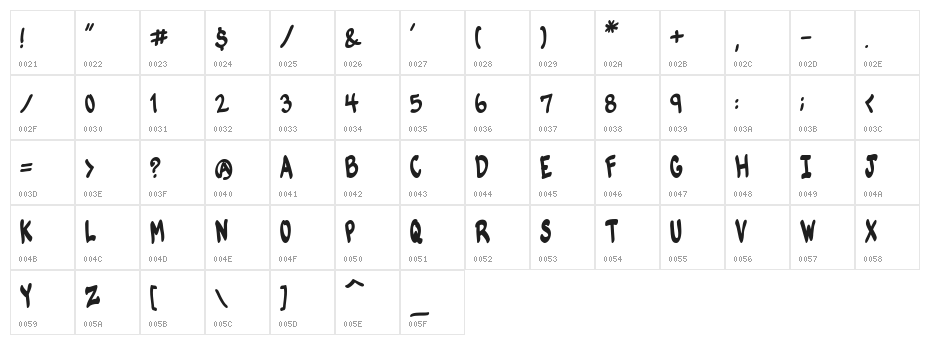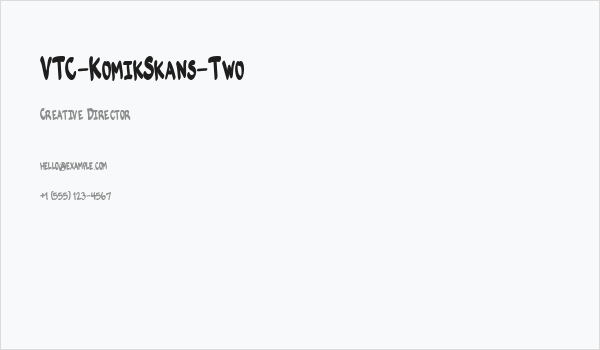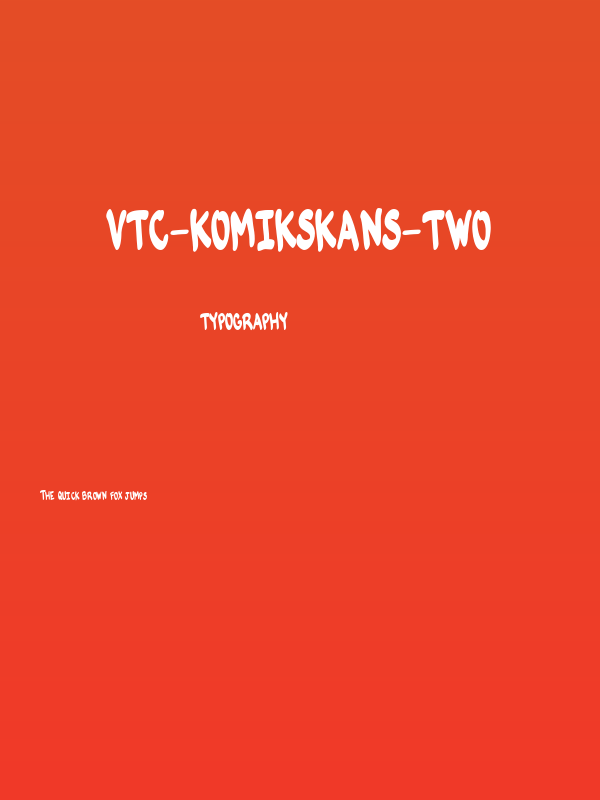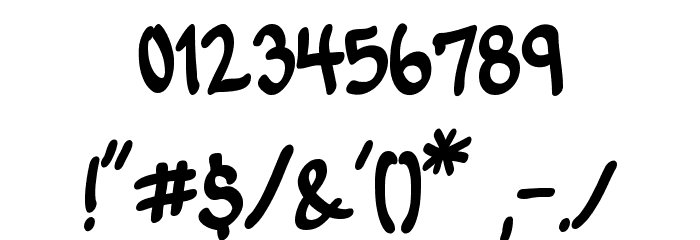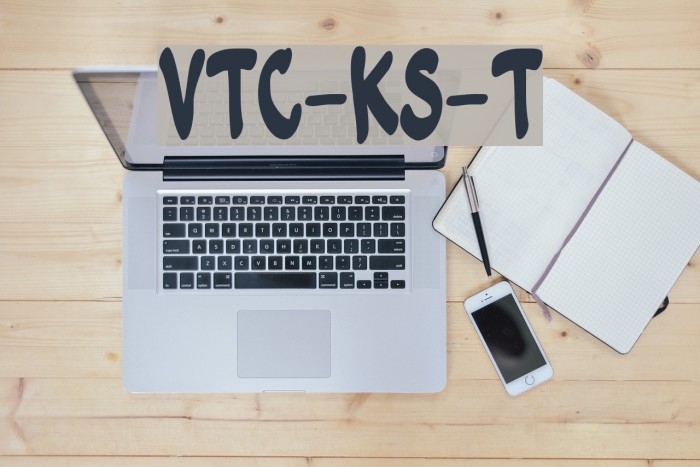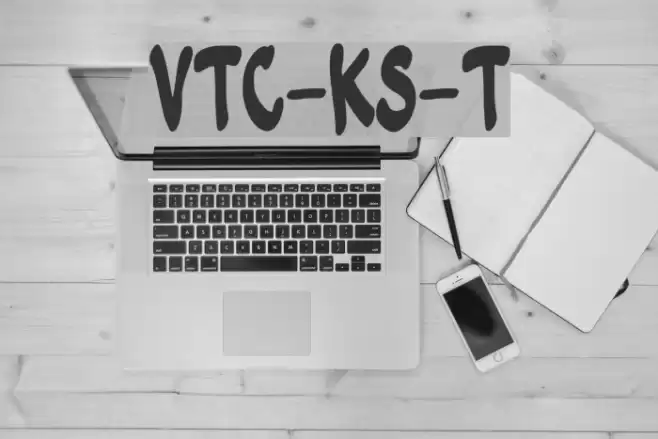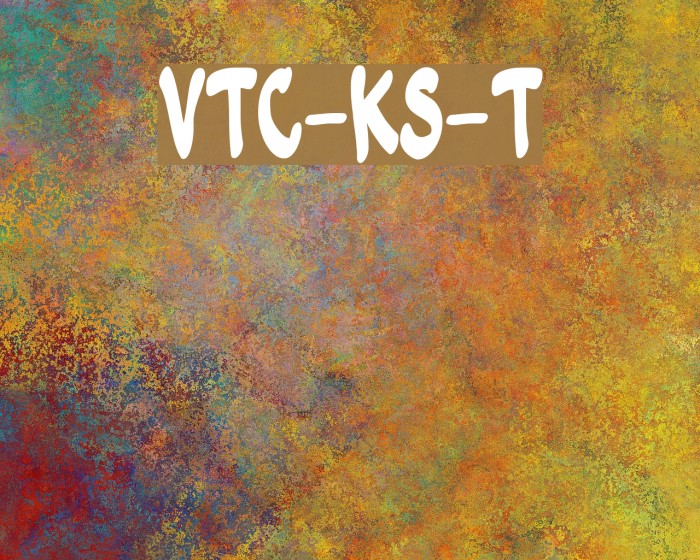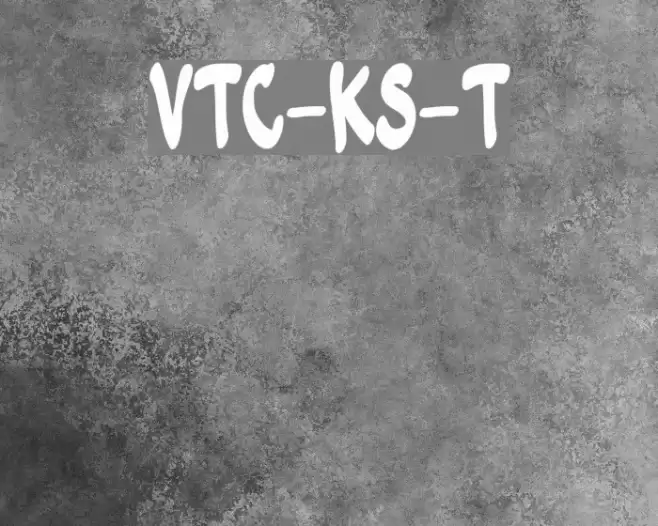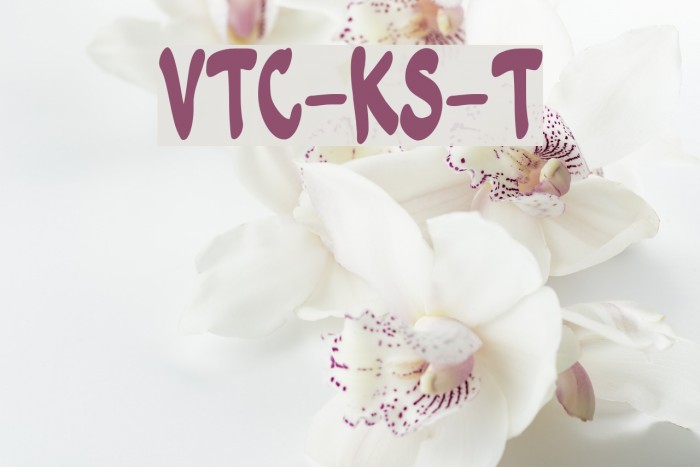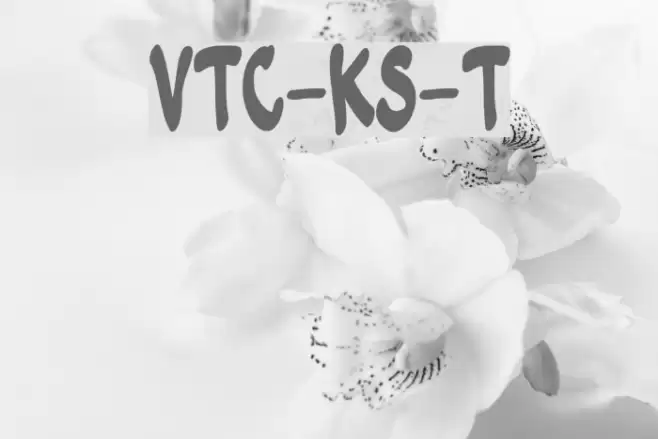
VTC-KomikSkans-Two Font
| Stil general | Playful, Comic |
| Proiecte propuse | Perfect for comic books, children's books, playful branding, posters, and any project needing a fun, informal touch. |